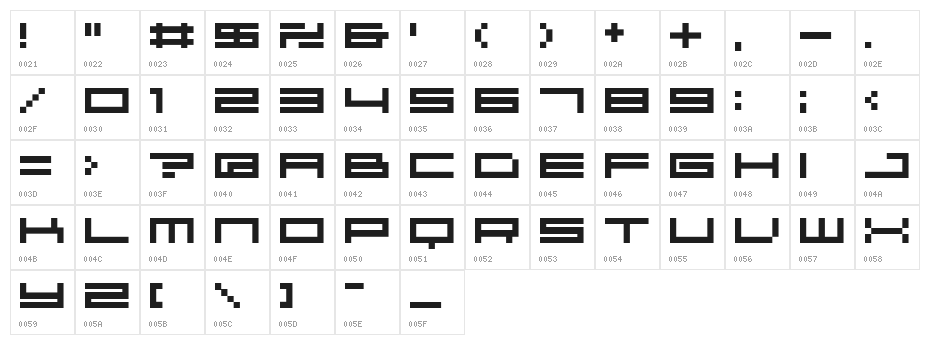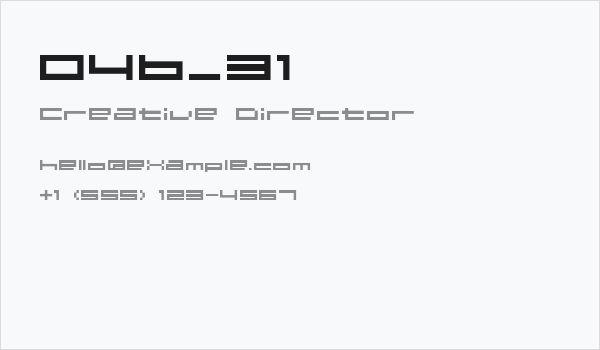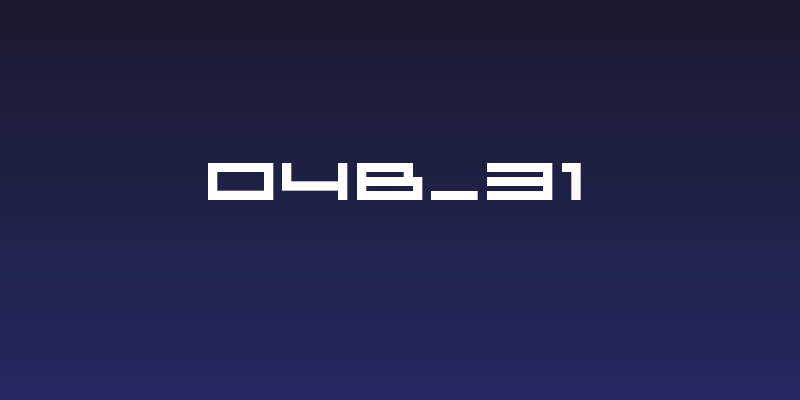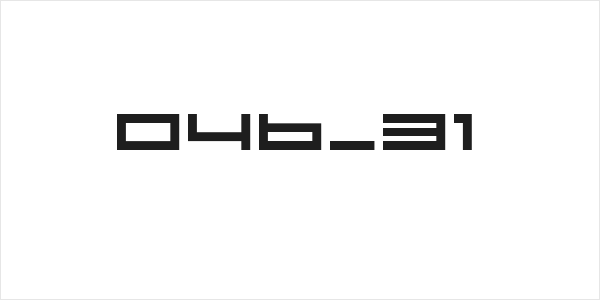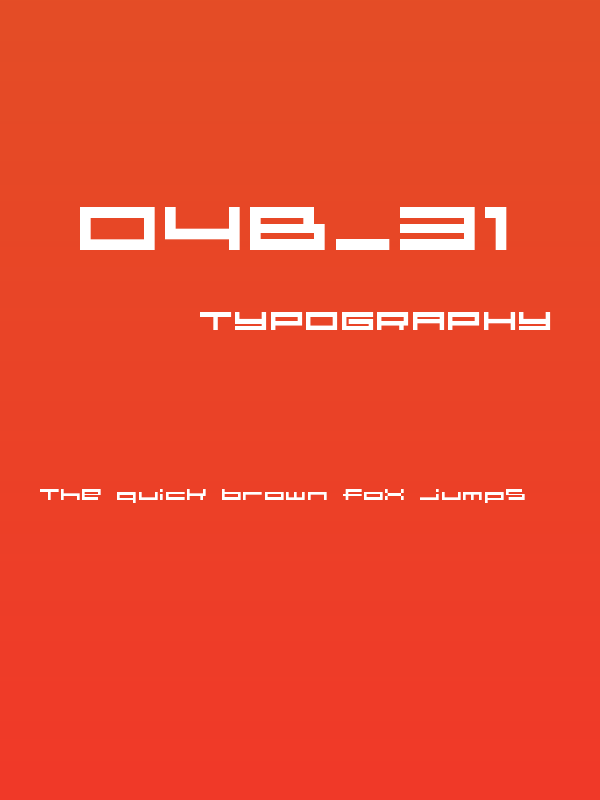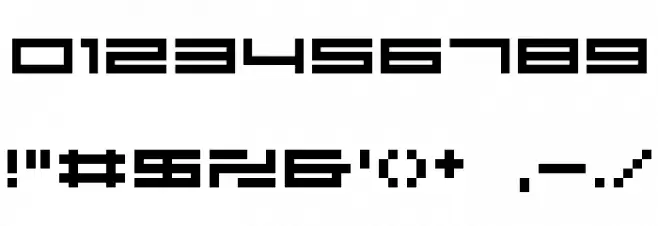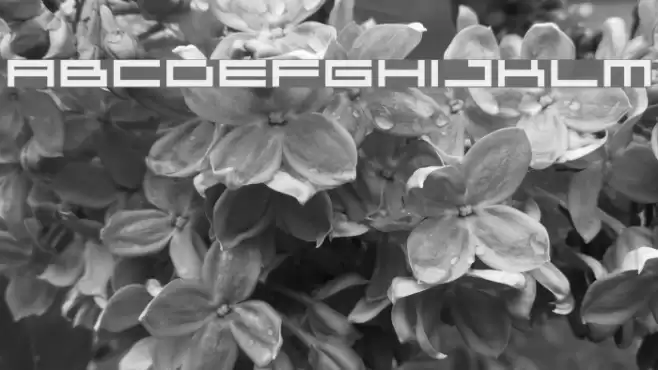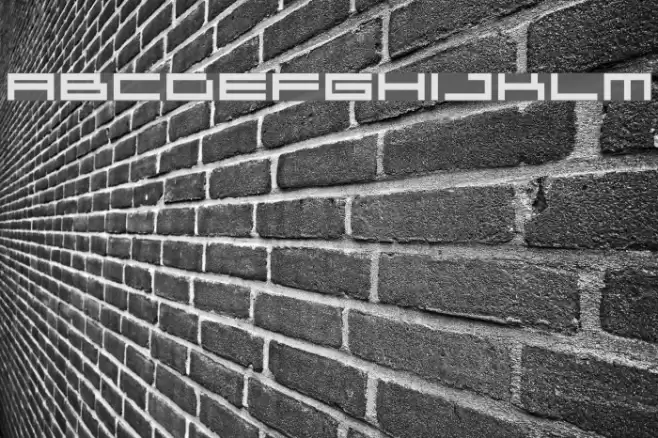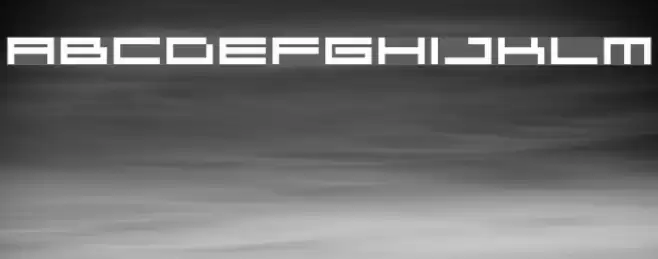
04b_31 Font
| Style général | Retro, Digital |
| Cas d'utilisation | Logos, Headlines, Digital interfaces |
| Projets proposés | Ideal for retro video games, digital art projects, tech-themed posters, and any design requiring a nostalgic digital aesthetic. |